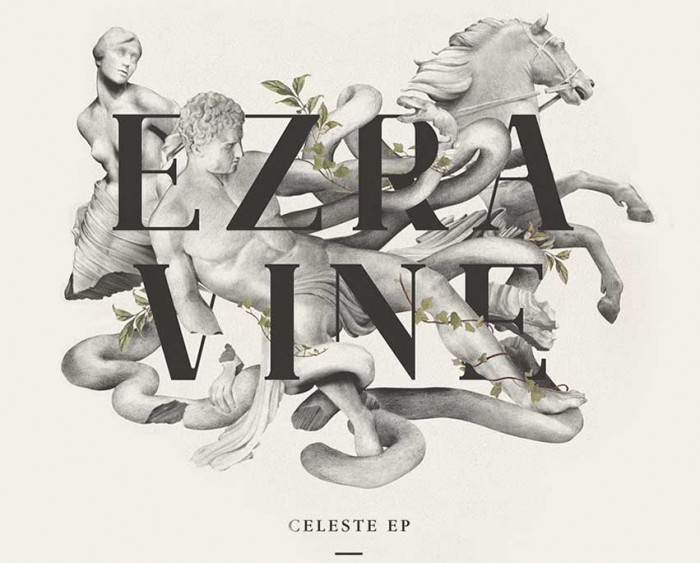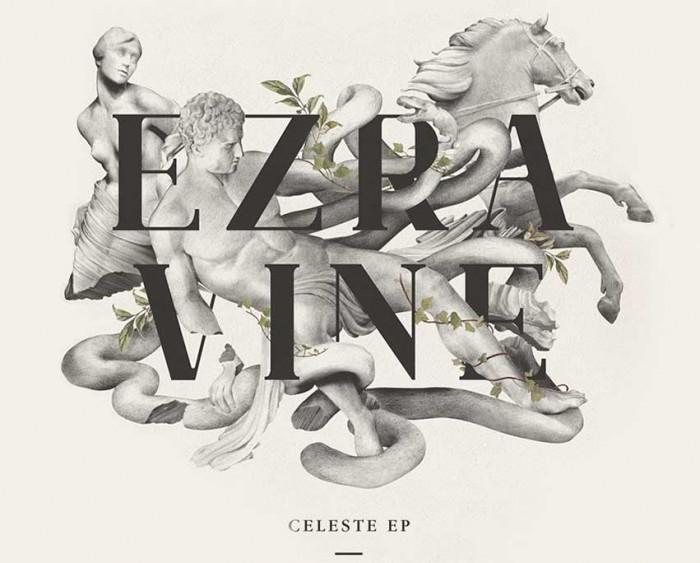
Schriftart vom EP Cover von Ezra Vine
Ich such die Schriftart von dem EP Cover von Ezra Vine (siehe Anhang). Es hat kontrastreiche Strichstärken und Serifen. Die Schriftart hat starke Ähnlichkeiten mit der Bodoni und Didot.